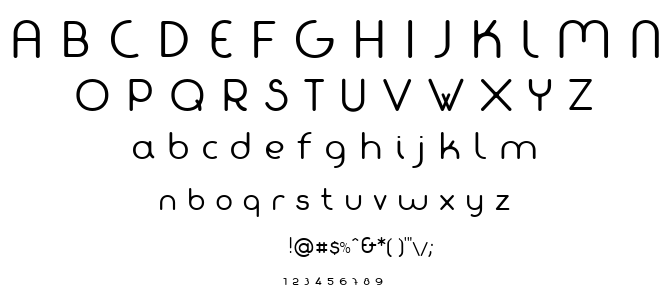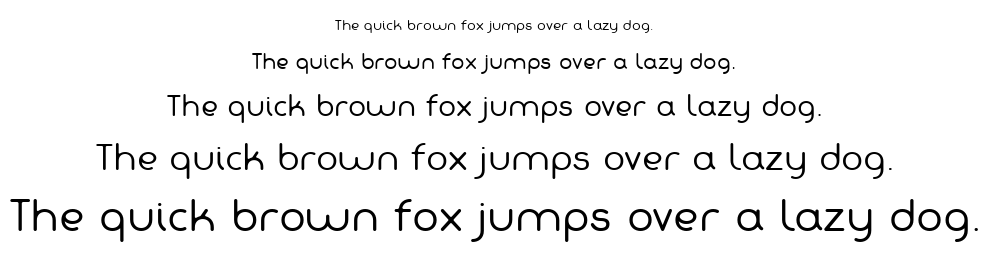
Esta tipografía fue mi primer contacto con diseño de tipos. Es una fuente para uso en grandes tamaños o display pues el tema del kerning y otras cuestiones de construcción no están cuidados. A cambio, la tipografía tiene 720 glifos diseñados con mucha confusión, y es por este potaje de letras y símbolos que la he llamado Fabada.